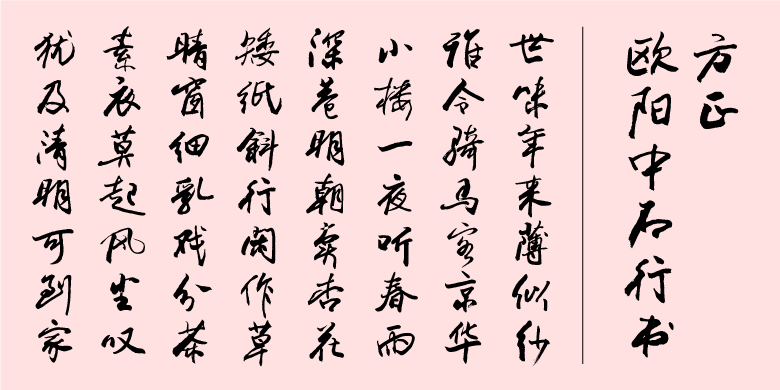
方正欧阳中石行书
字体品牌: 方正字库 中华精品字库 整理/设计:欧阳中石 字体分类:常规书写·毛笔 字体属性:精品字 字符集:简繁扩展(GBK) 发布时间: 2023
关于欧阳中石:
我国著名学者、教育家、书法家,中央文史馆馆员,中国人民政治协商会议全国委员会第八、九、十、十一、十二届委员,中国书法家协会原顾问、当代书法学科建设重要开拓者。欧阳中石在艺术领域博学多优:精于诗词曲联,擅长写意绘画,京剧为奚派嫡传。在书法上,他各体兼综而汇通于行草。以东晋书风为宗,博采周金汉石、碑刻法帖之长,形成刚健温润、飘逸沉稳、灵动厚重的独特艺术风格,在海内外享有盛誉。
字体特征:
刚健温润、飘逸沉稳、灵动厚重。